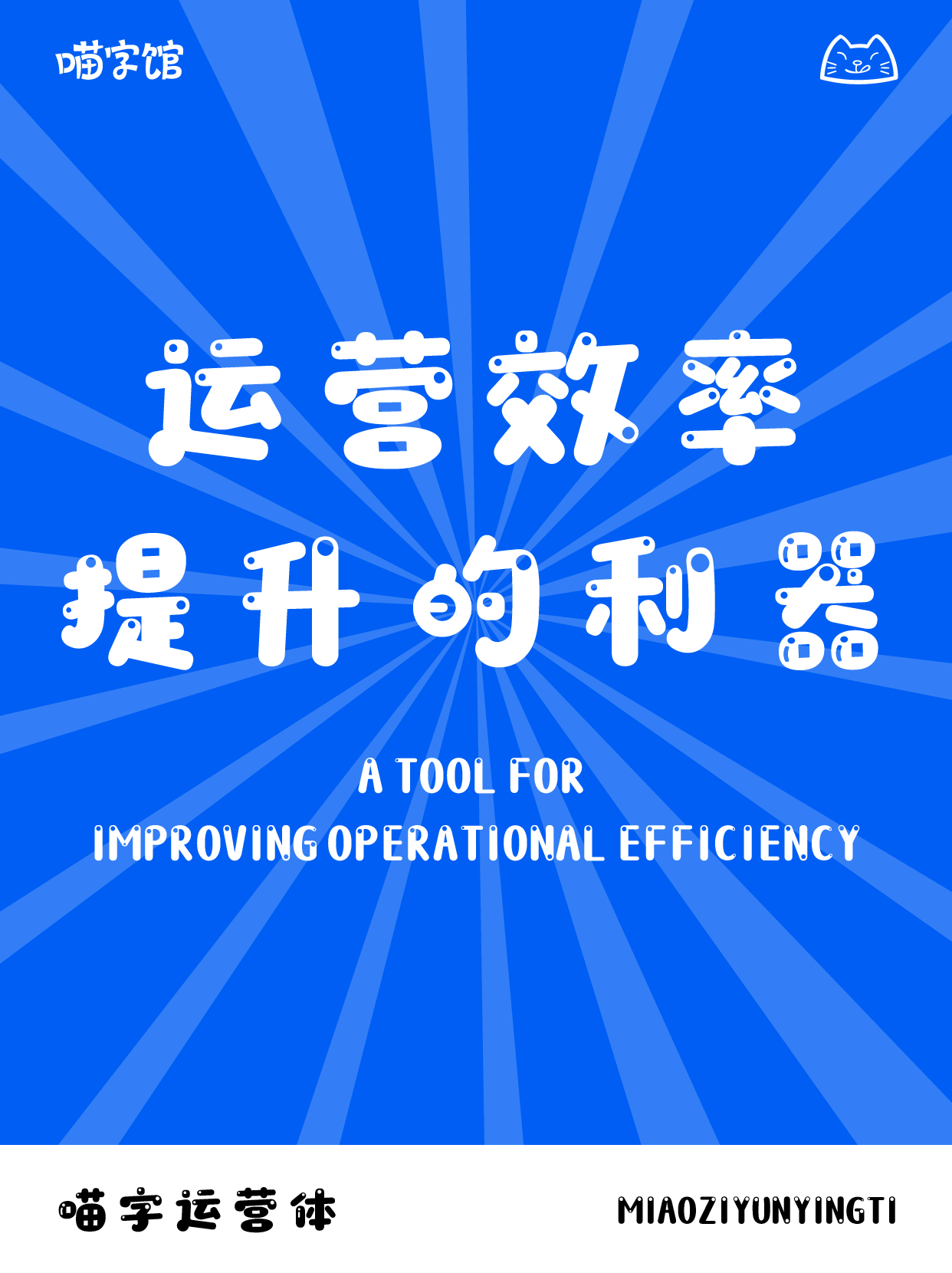
手绘风格绘本字体精选,为故事添彩
励字志向黑简 中粗,
志向黑采用圆体与黑体的融合,在笔画拐角增加适当的外圆角的手法在整体稳重大气的字形中增添少许灵动,使字体字面充实,结构稳定之余,更适配屏显的使用。
喵字运营体,
喵字运营体是一款专为社企运营人员量身打造的行业定制级字库。随着市场竞争的加剧,企业对于品牌传播的要求越来越高。字体作为品牌视觉识别系统的重要组成部分,其独特性和专业性对于企业的商业转化具有至关重要的作用。然而,市面上大多数字体库无法满足企业运营人员的特定需求,导致品牌传播效果大打折扣。为了解决这个问题,我们深入调研了企业运营人员的实际需求,结合行业特点,研发了喵字运营体。
也字工厂猛犸手迹,
也字工厂猛犸手迹是一款“看似随性,实有章法”的手写字体。猛犸手迹起笔如蜻蜓点水,运笔流畅、力度均衡,折笔处未继承驻笔转向的常规操作,任其笔画随性书写,落笔飘逸、适可而止;从笔迹观感来看,笔法看不出太多规则和限制,反倒让人觉得轻松自由,就像动画电影《冰河世纪》里面的主角之一,体型庞大,性格却温和可亲的猛犸象。这是一款非常适用于娱乐向应用场景的手写体哦~